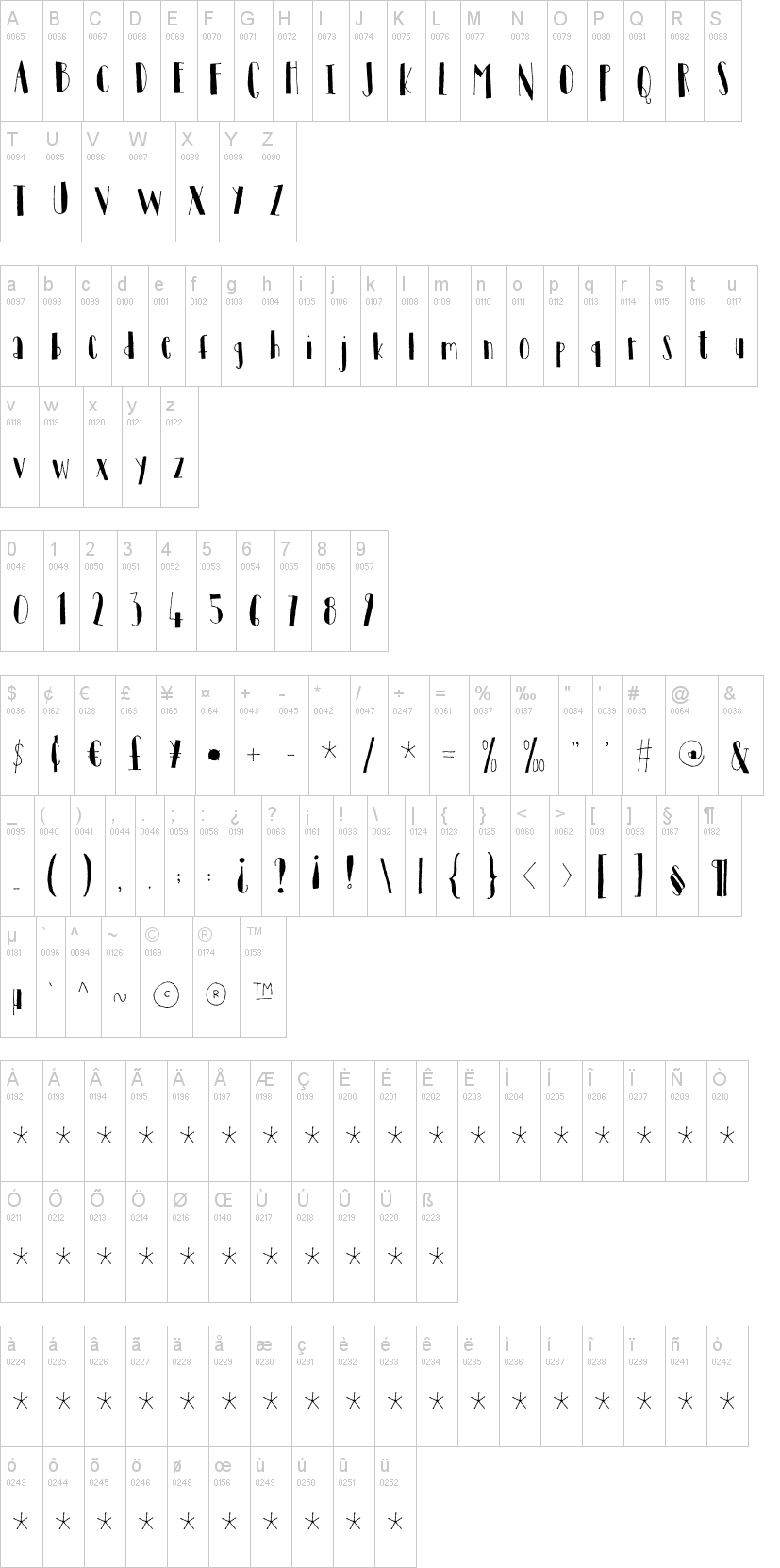
Tantamount是一款由Fontfabric创作的简洁大气的多功能字体,它可以用于多种用途,从印刷到网页设计。它的字体设计简单,易于阅读,可以满足大多数多媒体项目的需求。它的字体结构也很稳定,可以用于多种设计目的,比如标题、标签、标语等。Tantamount字体的设计风格简洁、大气,可以满足大多数设计需求。内容介绍
Tantamount是一款非常不错的手写艺术字体,具有很好的视觉感,适合于文化类的宣传设计、商业类品牌的广告和产品包装设计以及个性化文字排版等较多场景。